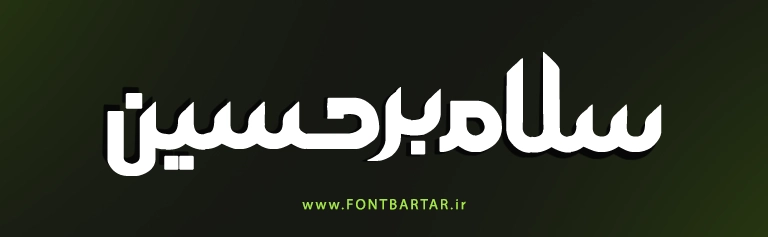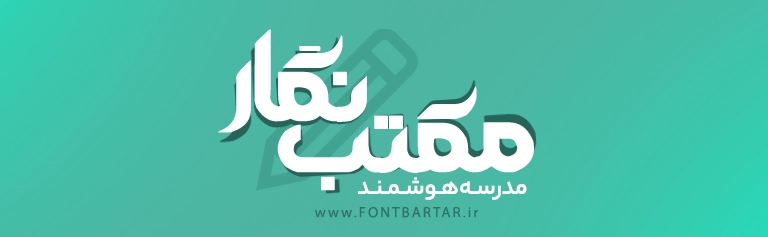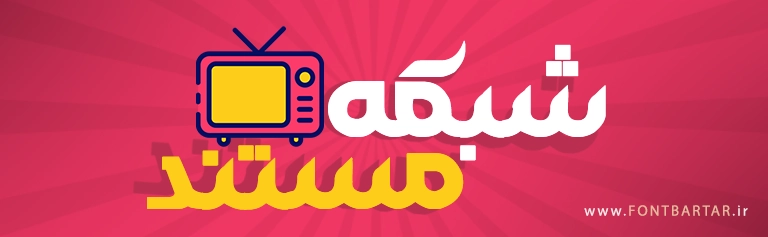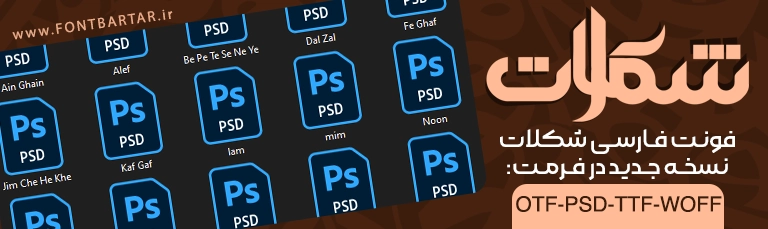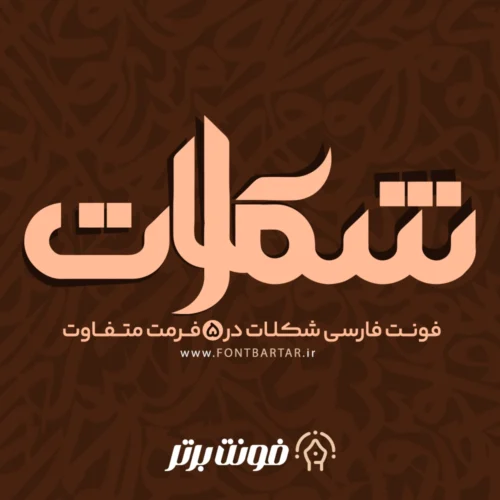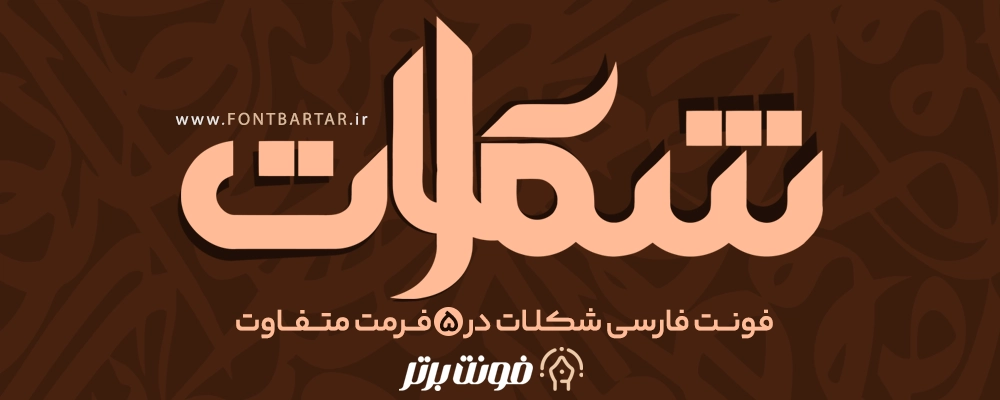
فونت لوگوتایپ و فونت تایپوگرافی شکلات
فونت شکلات یکی دیگر از فونت های طراحی لوگوتایپ و تایپوگرافی می باشد، فونت فارسی شکلات با طراحی حرفه ای و انعطاف پذیر می باشد و این امکان را فراهم می آورد که به راحتی بتوانید حروف را در کنار هم قرار دهید، با خرید فونت شکلات می توانید بدون هیچگونه دانشی لوگو تایپ طراحی کرده و تایپوگرافی های زیبایی انجام دهید و از آن کسب درآمد کنید.
- شامل تمامی حروف از الف تا ی در تمامی حالت ها